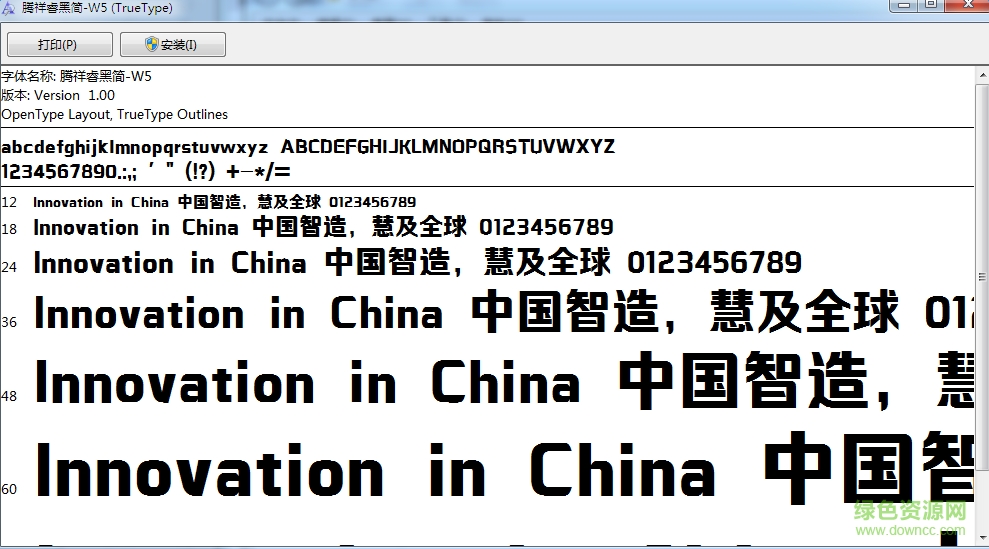
騰祥睿黑簡W5是一款黑體電腦字體,塔形頓點(diǎn)、撇點(diǎn)和部分折筆處外圓角的設(shè)計(jì),使得字形看上去內(nèi)斂、圓潤、弱化了黑體尖銳和張揚(yáng)的感覺,喜歡的朋友歡迎來綠色資源網(wǎng)下載!
騰祥睿黑簡W5為粗黑一款為了調(diào)整黑白空間在筆畫交叉處特別做了墨跡處理,使整體筆畫看起來既粗壯醒目又清晰易讀,筆型嚴(yán)謹(jǐn)規(guī)范,粗壯、醒目適用于標(biāo)題、大標(biāo)題、海報及大型廣告等。